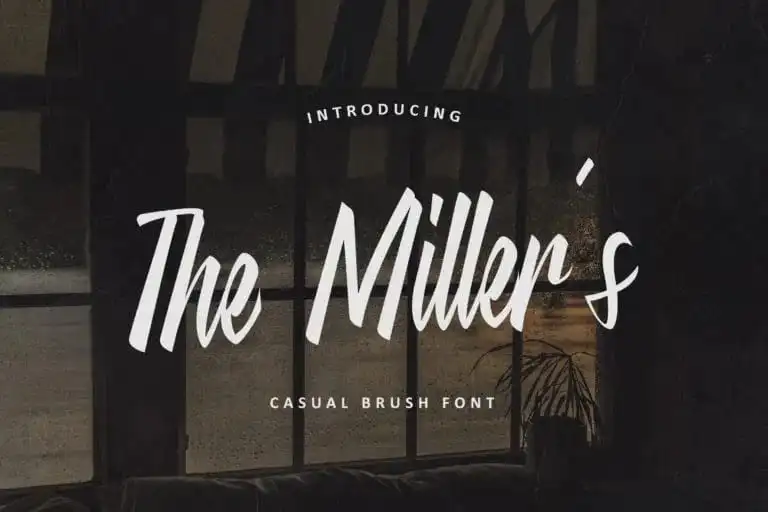
The Miller’s Script Font
A Miller’s Script Font é uma elegante tipografia moderna que une a encanto do estilo clássico da escrita à sua versão contemporânea. Escrevendo com um pincel, essa fonte oferece um charme casual que a torna imediatamente acessível e amigável. Seu aspecto natural e fácil de ler torna-a uma opção perfeita para aplicar em logotipos, desenhos a mão ou design de roupas. A Miller’s Script Font é uma escolha versátil que pode ser adaptada para inúmeras necessidades gráficas, desde identificações de marca até ilustrações e estampas exclusivas.